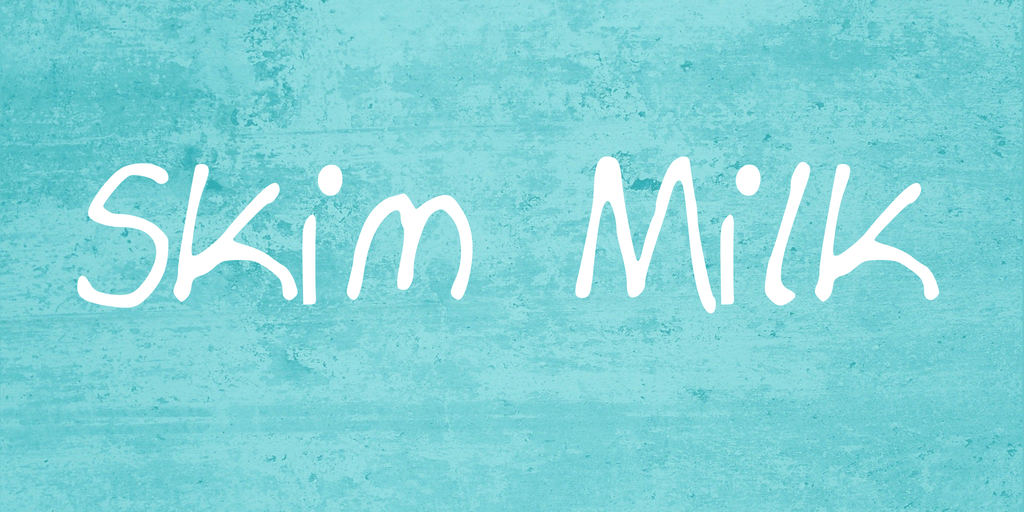
Skim Milk Font – Download Grátis
A Skim Milk Font é uma delicada e elegante fonte script desenvolvida por Hamilton, perfeita para quem busca uma aparição minimalista e envolvente em suas criações digitais. Com linhas finas e curvas suaves que se movem como um sonho sobre o papel, esta fonte oferece a sensação de calma e tranquilidade que faz dela uma escolha ótima para projetos pessoais ou amigáveis. Suas formas leves e delicadas garantem um acabamento harmonioso em elementos do design digital que exigem uma aparência minimalista, como banners de vídeos, títulos de modificações ou até mesmo cartões de aniversário. Hamilton criou a Skim Milk Font para ser usada na hora certa – em seus projetos pessoais e não-mercados. Como instruções do designer Hamilton são claras: evite o uso da fonte em qualquer material que possa vir a gerar lucro, como um título de vídeo monetizado. Sua visão atenta à necessidade de respeitar os limites dos criadores ao fornecer materiais de uso pessoal. A Skim Milk Font é uma delícia para o olho e uma fonte segura para quem deseja adicionar um toque naturalmente elegante aos seus trabalhos digitais.